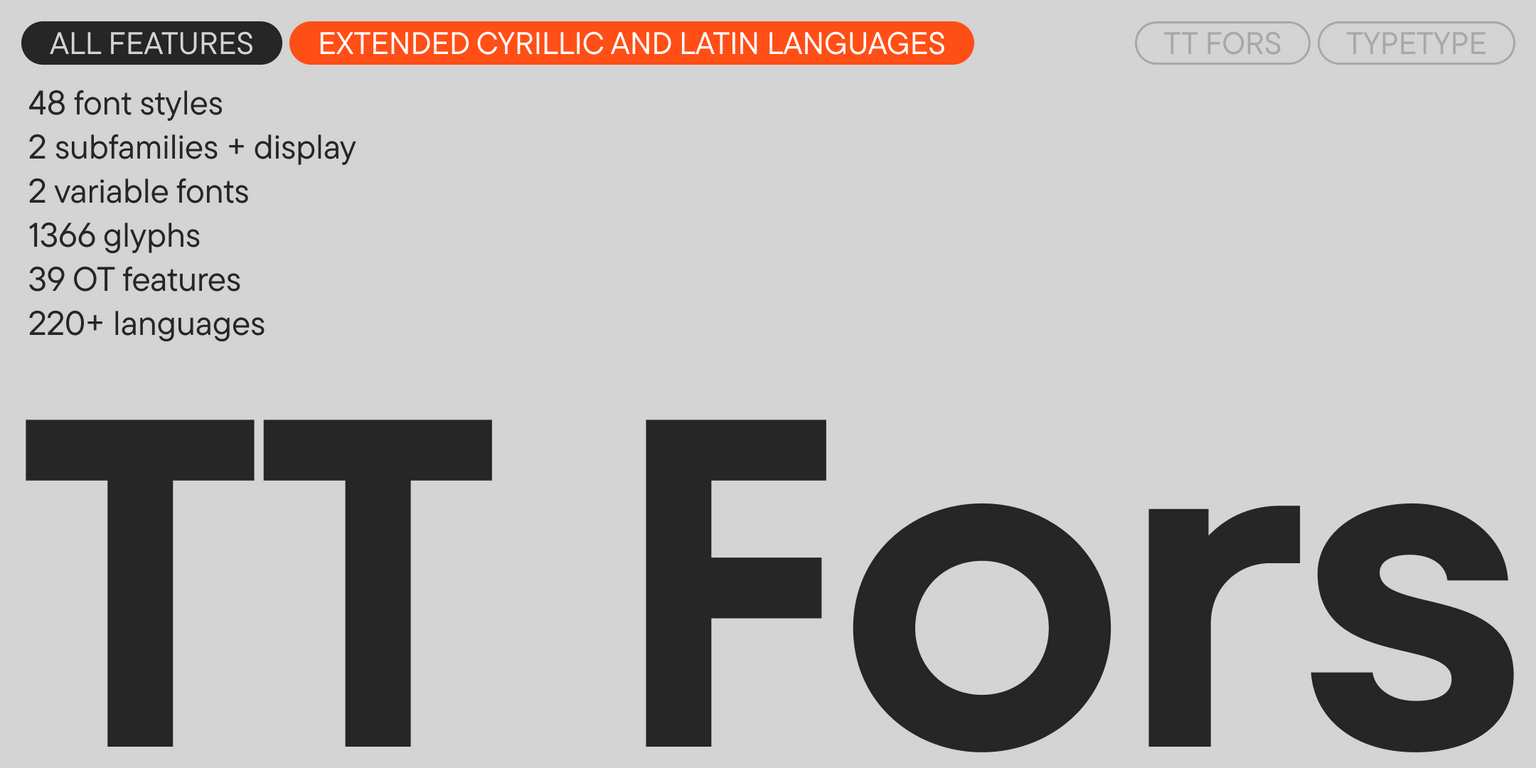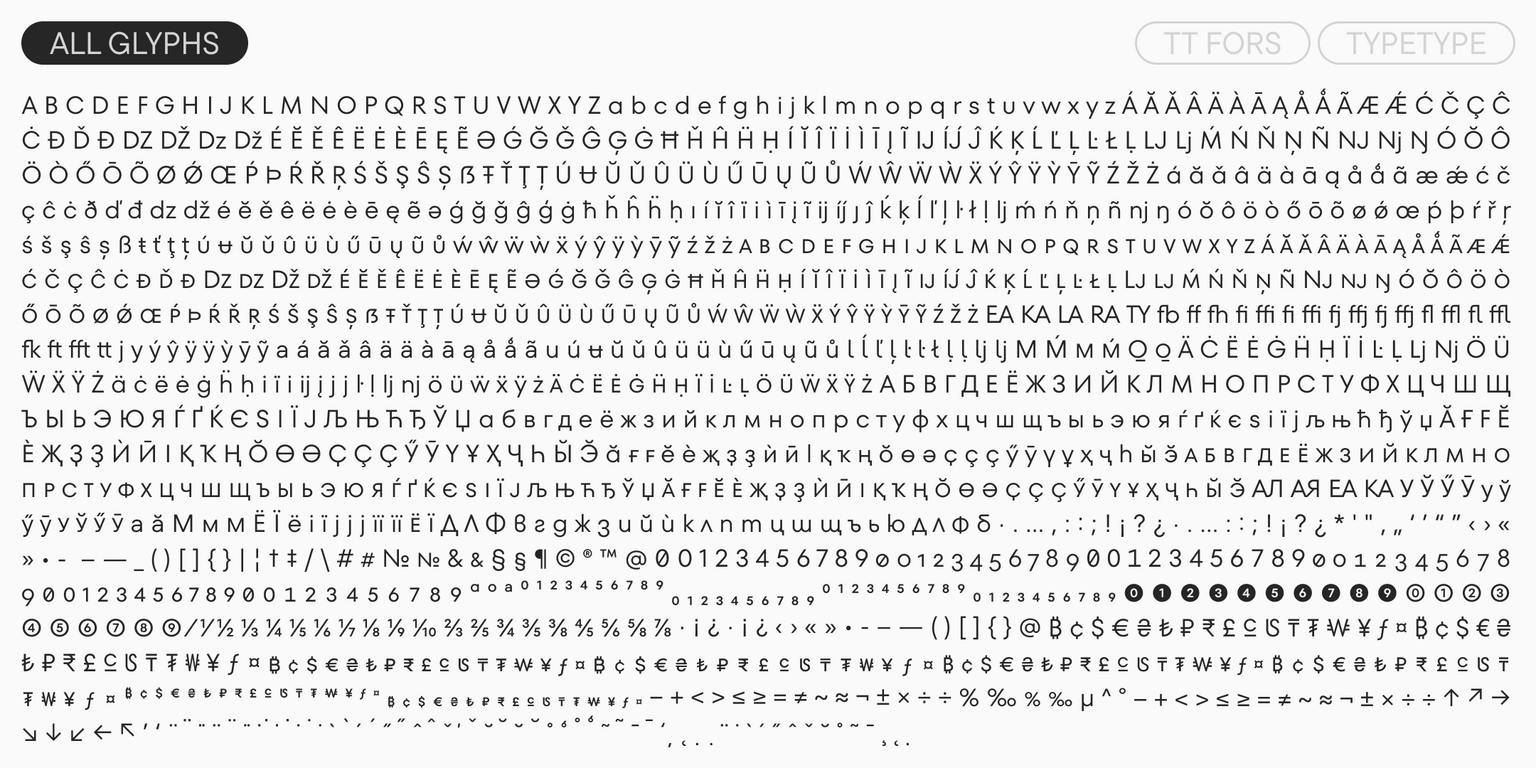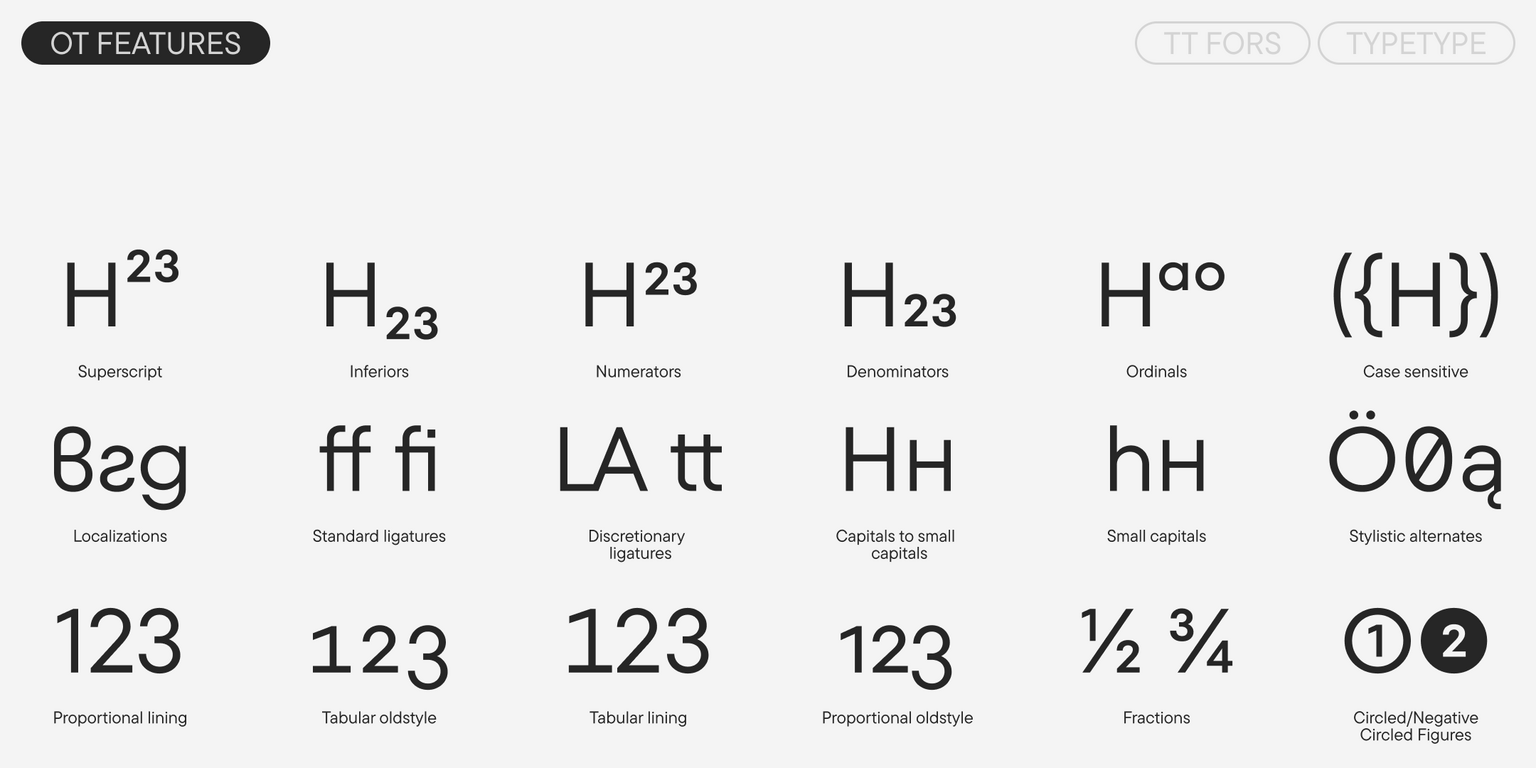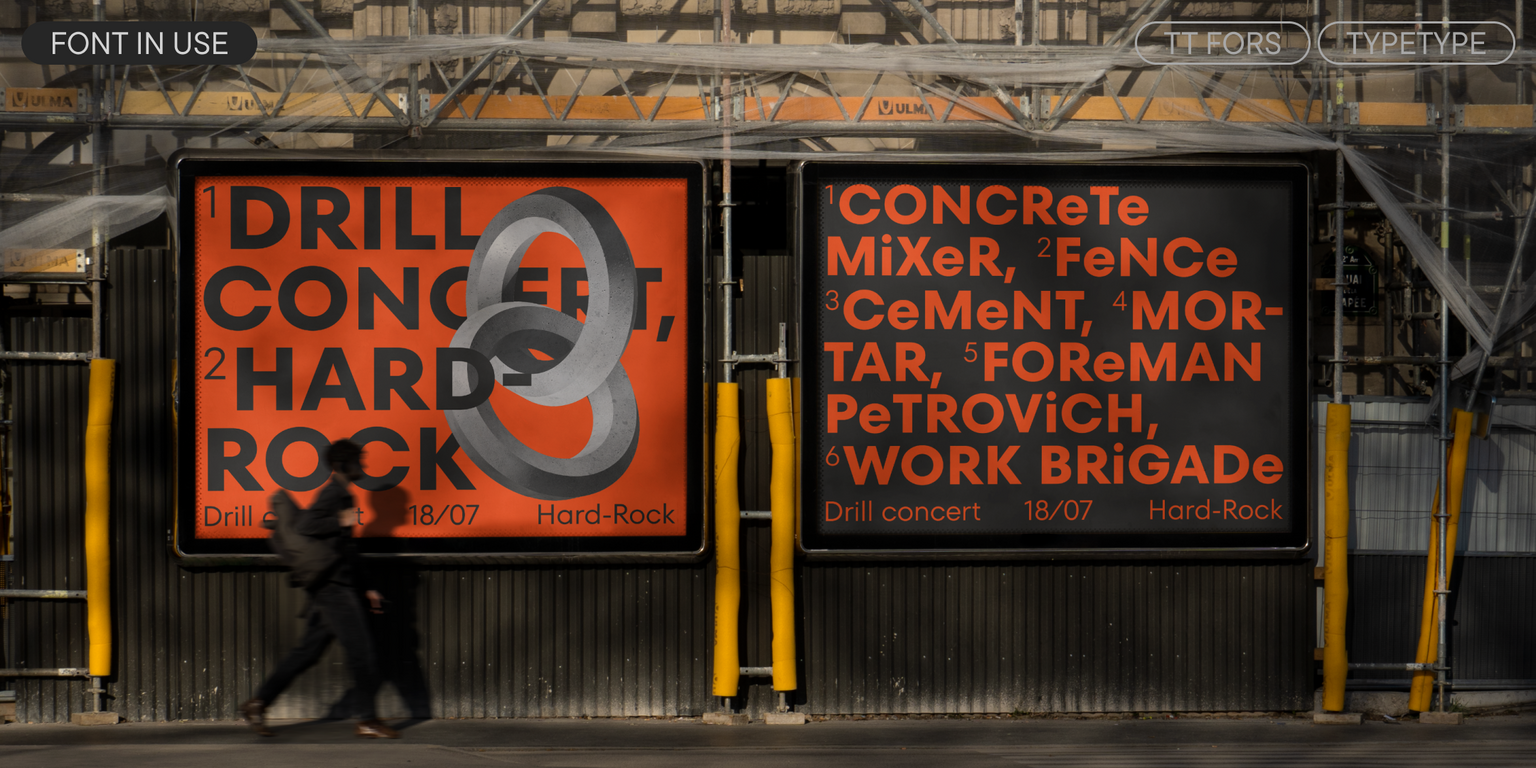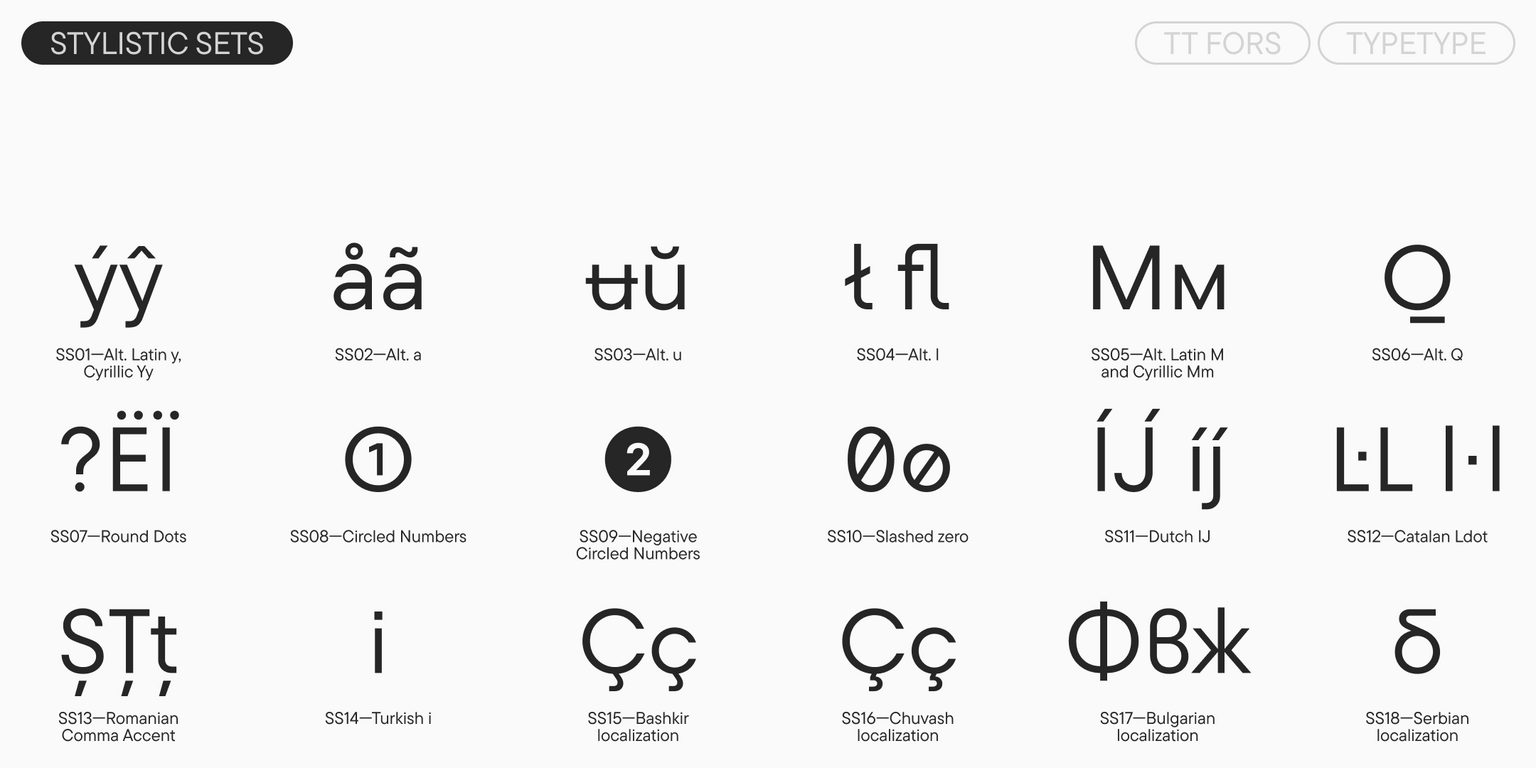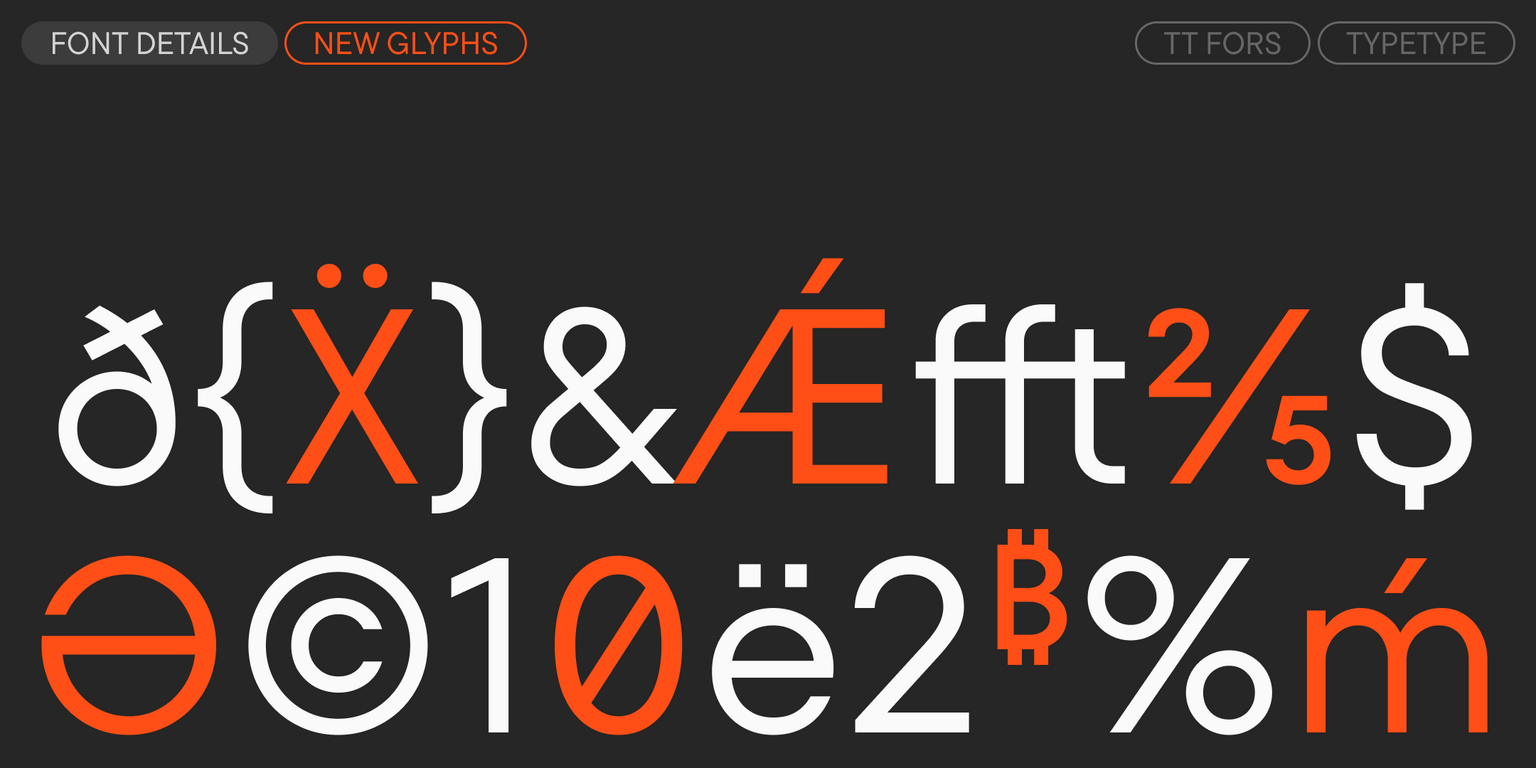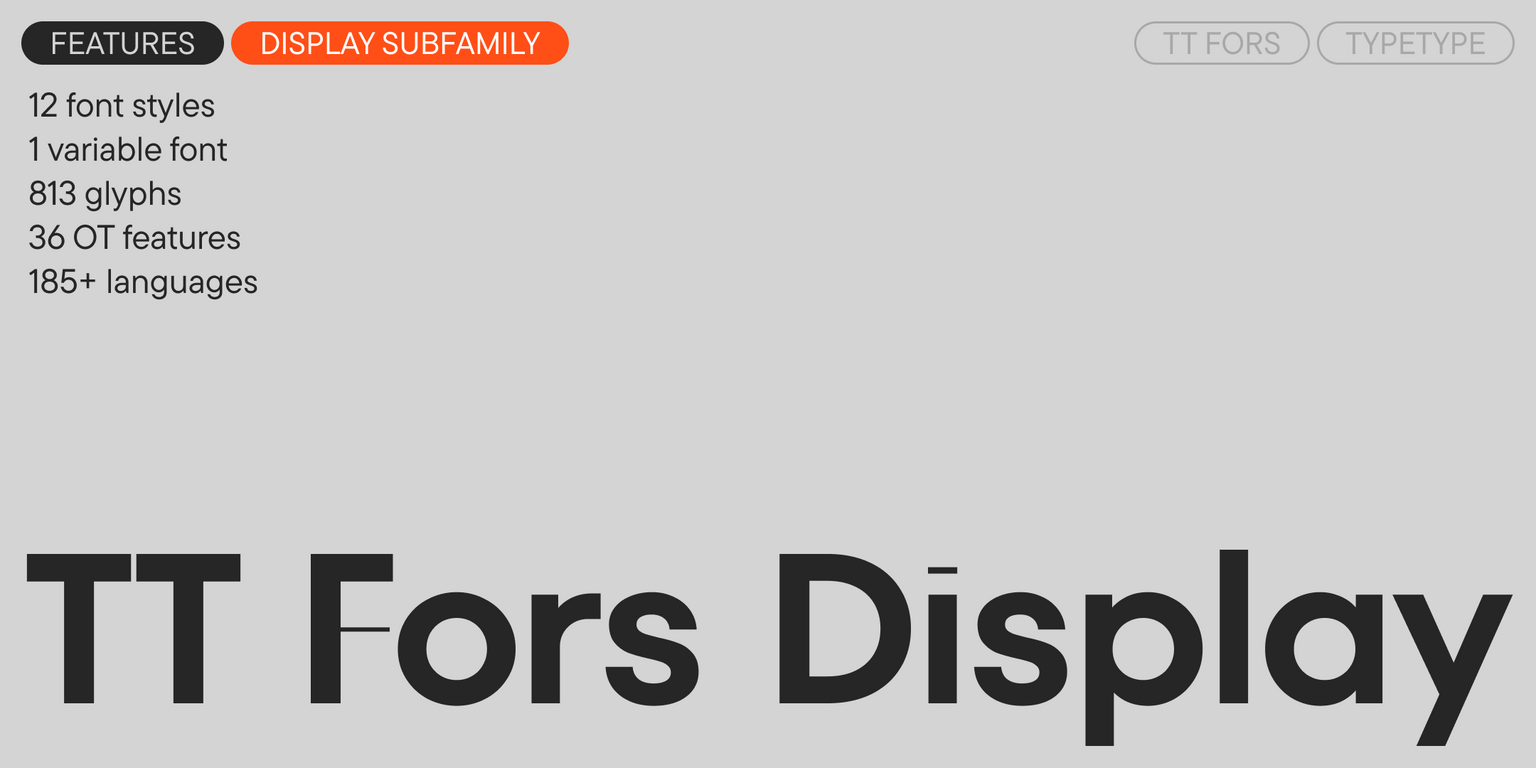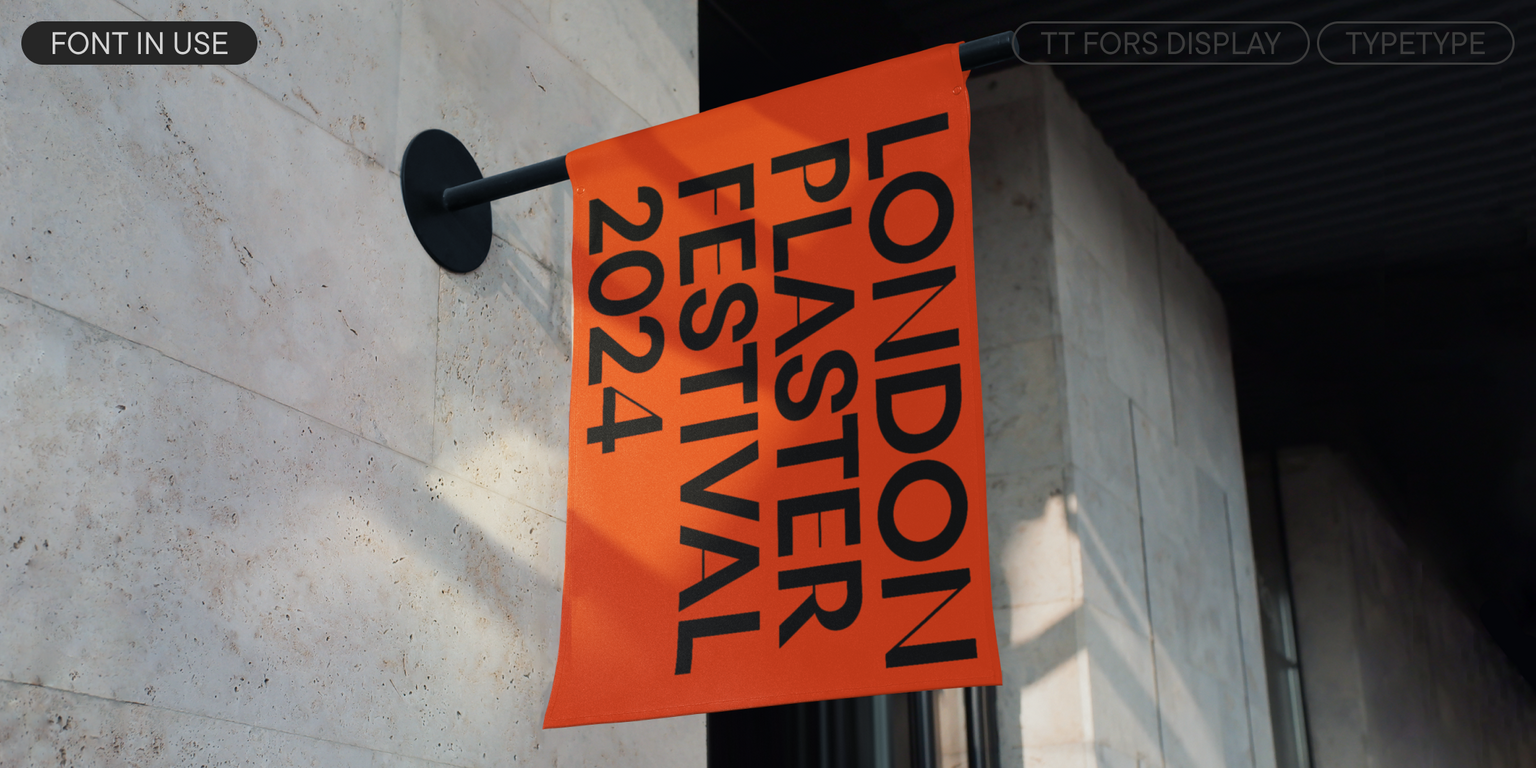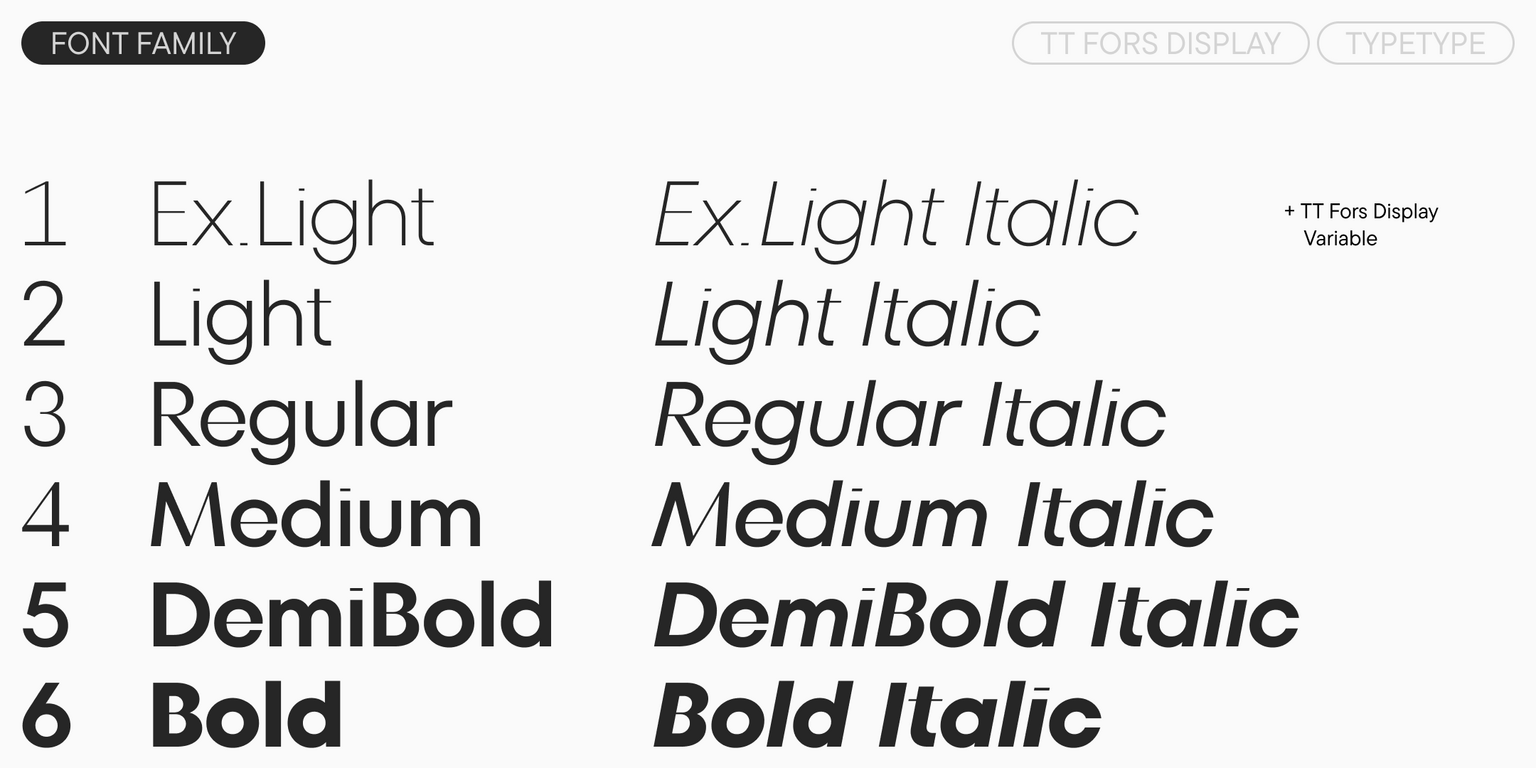
TT Fors
TT Fors — ТТ Форс
Произносится «ТТ Форс». «Fors» — производное слово от for, в переводе с английского «для». Буквы «TT» являются аббревиатурой названия компании.
TT Fors — стильный и лаконичный геометрический гротеск с выверенными формами. Его можно использовать и в интерфейсах, и для создания акцентов.
TT Fors
TT Fors — современный геометрический гротеск
TT Fors
Создание шрифта TT Fors вдохновлено глубоким изучением геометрических гротесков первой трети XX века и их влияния на визуальную культуру и дизайн прошлого столетия. Наша цель заключалась в разработке универсальной и функциональной гарнитуры, которая, сохраняя связь с наследием великих типографов прошлого, отвечала бы требованиям современности и решала актуальные задачи. В 2024 году мы представили масштабное обновление семейства TT Fors, ключевым элементом которого стала узкая версия — TT Fors Condensed. Как и основное семейство, она включает 18 начертаний, что значительно расширяет возможности для дизайна. Кроме того, в вариативную версию TT Fors была добавлена третья ось — Width, позволя- ющая динамически изменять ширину шрифта от узкой до стандартной прямо в процессе работы. В 2025 году мы продолжили развивать шрифт, расширив латинский и кириллический алфавиты новыми глифами. Это обновление увеличило языковую поддержку TT Fors на 57 языков, сделав его еще более универсальным и доступным для дизайнеров по всему миру.
В семействе три оси вариативности — ширина, толщина и наклон
TT Fors в дизайне
О гарнитуре TT Fors
Поддержка языков 220+
Встречайте легендарный TT Fors в версии 2.100!
Функциональный и эстетичный шрифт из коллекции «базовых» гарнитур TypeType стал еще лучше: теперь в нём ещё больше знаков, фич, стилистических альтернатив и языков.
TT Fors — геометрический гротеск с нейтральным характером и выверенными пропорциями. Шрифт дополняет линейку универсальных гротесков от TypeType, в которую уже входят такие семейства, как TT Norms® Pro, TT Commons™ Pro, TT Hoves Pro, TT Interphases Pro и TT Firs Neue.
Вдохновением для создания TT Fors послужило исследование геометрических гротесков начала-середины 20 века и анализ их влияния на визуальную культуру и дизайн того времени. Мы стремились создать гарнитуру, которая, сохраняя связь с наследием великих типографов прошлого, отвечала бы требованиям современности и решала актуальные задачи.
Знаки в шрифте разноширинны. Формы максимально приближены к базовым геометрическим фигурам (круг, треугольник, квадрат). Круглые знаки тяготеют к правильному кругу, а остальные имеют более узкие пропорции. Достаточно высокие строчные знаки делают шрифт ещё более функциональным. А выверенные геометрические формы и единые правила построения позволяют использовать TT Fors как в крупном, так и в очень маленьком кегле.
В дисплейной версии сохранилась лаконичность базовых начертаний, при этом добавились новые смыслы. Пропорции и формы знаков остались узнаваемыми, но появилась изюминка — символы с высоким контрастом. Набор стремится к равномерности, а слегка закрытые терминалы подчеркивают характер всей гарнитуры.